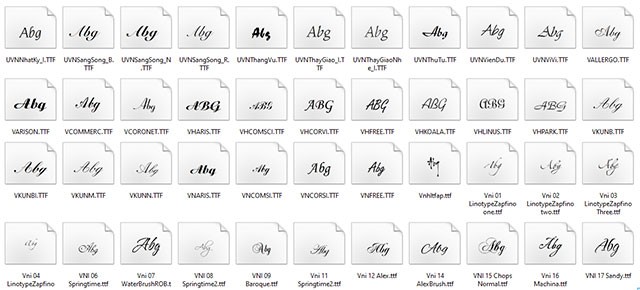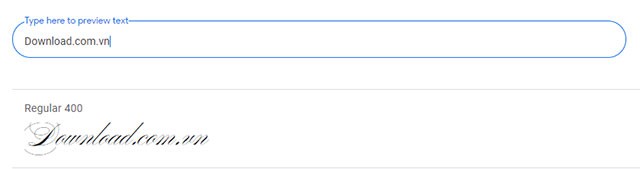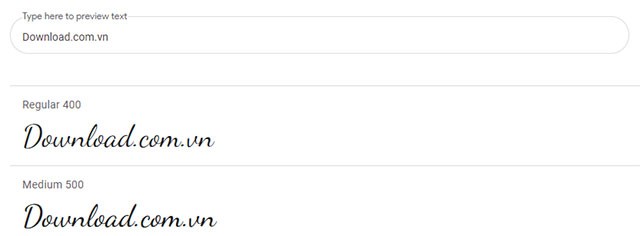
Tổng Hợp Font Chữ Viết Tay Đẹp Nhất
Giới Thiệu Chi Tiết
Bộ Font Chữ Việt Viết Tay: Giải Pháp Sáng Tạo Cho Văn Bản
Bộ font chữ tiếng Việt này là một bộ sưu tập các kiểu chữ mô phỏng chữ viết tay, được cung cấp miễn phí cho hệ điều hành Windows. Với bộ font này, người dùng có thể tự do sáng tạo các kiểu chữ đánh máy mang phong cách viết tay, tạo cảm giác gần gũi, thân thiện và độc đáo.
Bộ Font chữ viết tay
Sự Khác Biệt So Với Các Bộ Font Khác
Mặc dù Bộ Font tiếng Việt đầy đủ cũng bao gồm một số font chữ viết tay, nhưng bộ sưu tập này mang đến sự đa dạng và lựa chọn phong phú hơn. Bạn sẽ dễ dàng tìm thấy kiểu chữ ưng ý nhất để sử dụng.
Đặc biệt, bộ font này rất hữu ích cho các giáo viên, giúp họ viết mẫu chữ đẹp cho học sinh.
Nguồn Cảm Hứng Thiết Kế
Trong lĩnh vực thiết kế, yếu tố sáng tạo luôn được đề cao. Thay vì sử dụng các font chữ đơn giản, quen thuộc, bộ font chữ viết tay sẽ mang đến nguồn cảm hứng mới mẻ.
Dù không mang tính nghệ thuật cao như Font chữ thư pháp , font chữ viết tay vẫn tạo được thiện cảm và sự gần gũi với người đọc.
Bộ Font chữ viết tay tiếng Việt
Font Chữ Viết Tay Google
Google cũng đã phát triển một bộ font chữ tiếng Việt đơn giản, mang phong cách của Font chữ Google Sans. Bộ font này bao gồm 14 định dạng khác nhau với nét chữ viết tay uyển chuyển, hứa hẹn sẽ thu hút sự chú ý của độc giả.
Font chữ viết tay tiếng Việt do Google phát triển
Sức Hút Của Nét Chữ Viết Tay
Các nét chữ viết tay luôn có sức cuốn hút đặc biệt. Mỗi font chữ trong bộ sưu tập này đều mang một vẻ đẹp riêng, độc đáo.
Bạn có thể thỏa sức sáng tạo các bản vẽ, thiết kế để tạo điểm nhấn cá nhân.
Font chữ viết tay mô phỏng đẹp mắt dùng trong thiết kế